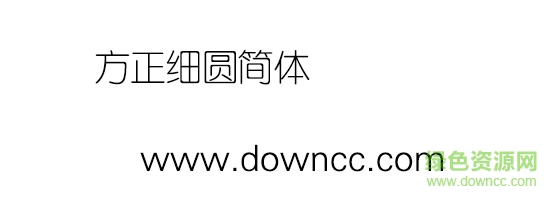
fzy1jw gb1 0是什么字體?fzy1jw gb1 0是一款非常好用的方正細(xì)圓簡(jiǎn)字體軟件,字體端正線條流暢,領(lǐng)用領(lǐng)域廣泛常用于廣告設(shè)計(jì)、圖文印刷、美工制作等多種領(lǐng)域,下載安裝即可使用。綠色資源網(wǎng)誠意推薦!
fzy1jw gb1 0字體適用于各種印刷出版物、雜志封面、海報(bào)、宣傳單,當(dāng)然更適合網(wǎng)頁設(shè)計(jì)上使用了!